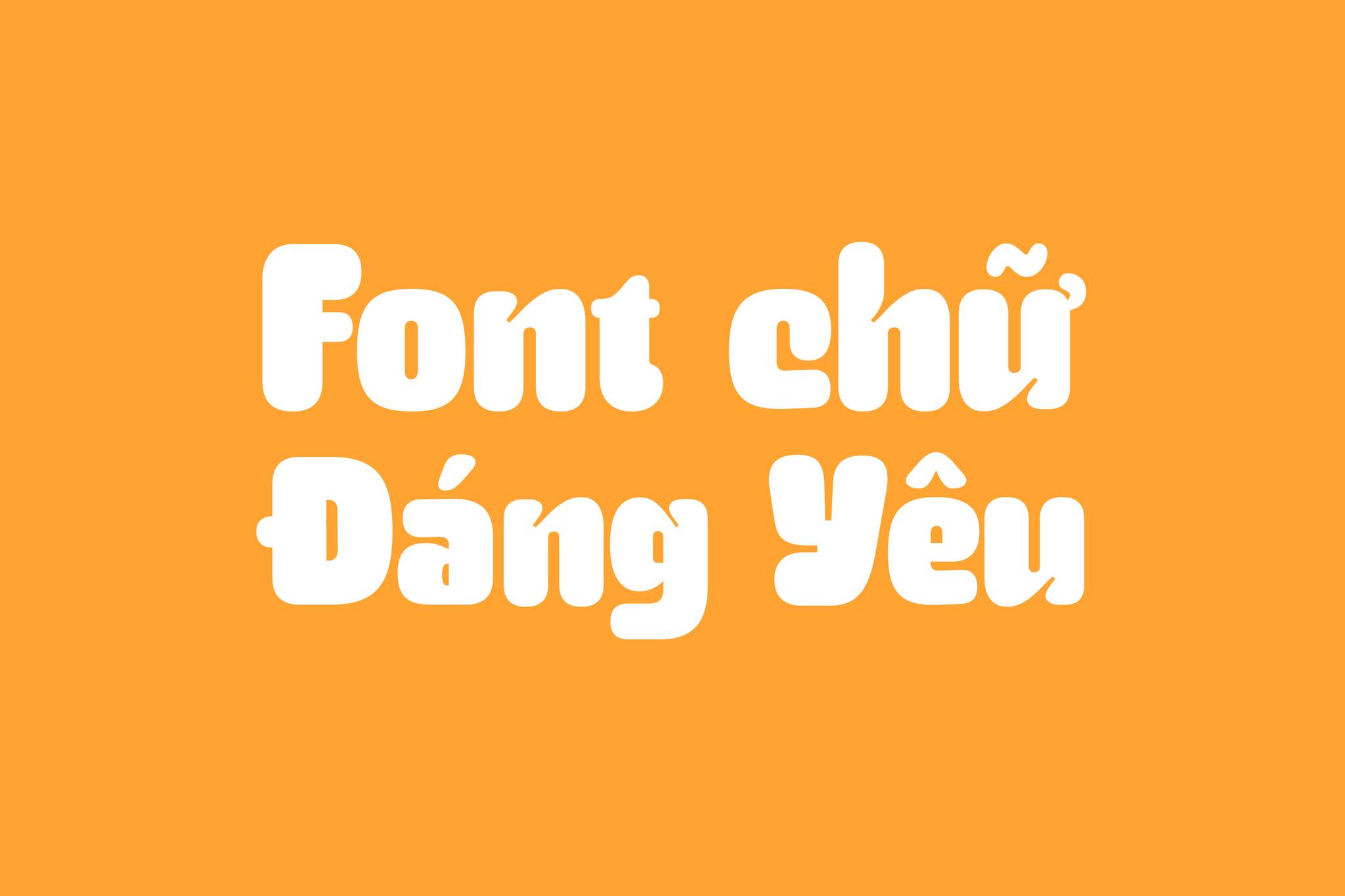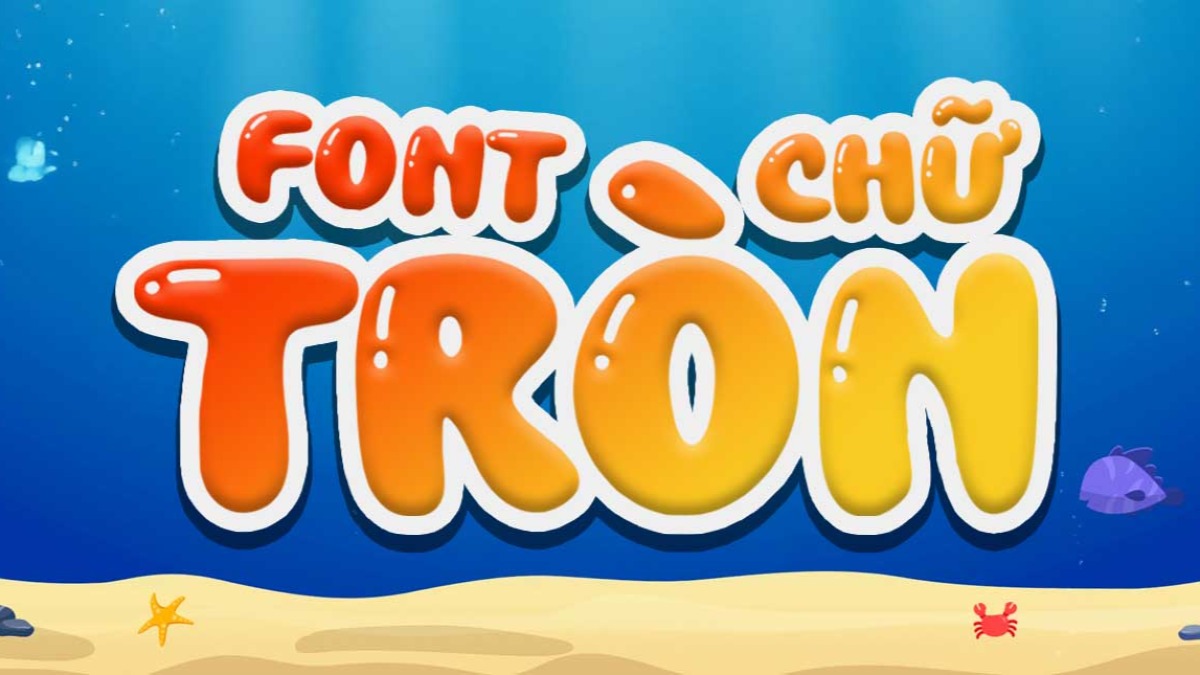
Font chữ tròn mập là nhóm phông chữ có cấu trúc nét dày (bold) và các góc chữ được bo tròn mềm mại thay vì để cạnh sắc nhọn. Trong thiết kế đồ họa, nhóm font này thường được sử dụng để tạo nên cảm giác thân thiện, vui vẻ và cực kỳ hiện đại. Doozypack.vn chia sẻ bộ font chữ bo tròn Việt hóa tuyển chọn, giúp bạn dễ dàng ứng dụng vào thiết kế bao bì, tem nhãn cho các sản phẩm dành cho giới trẻ hoặc trẻ em mà không lo lỗi hiển thị dấu tiếng Việt.
Tại sao font chữ bo tròn lại được yêu thích trong thiết kế bao bì?
Việc lựa chọn kiểu chữ ảnh hưởng trực tiếp đến tâm lý khách hàng khi nhìn vào sản phẩm lần đầu tiên.
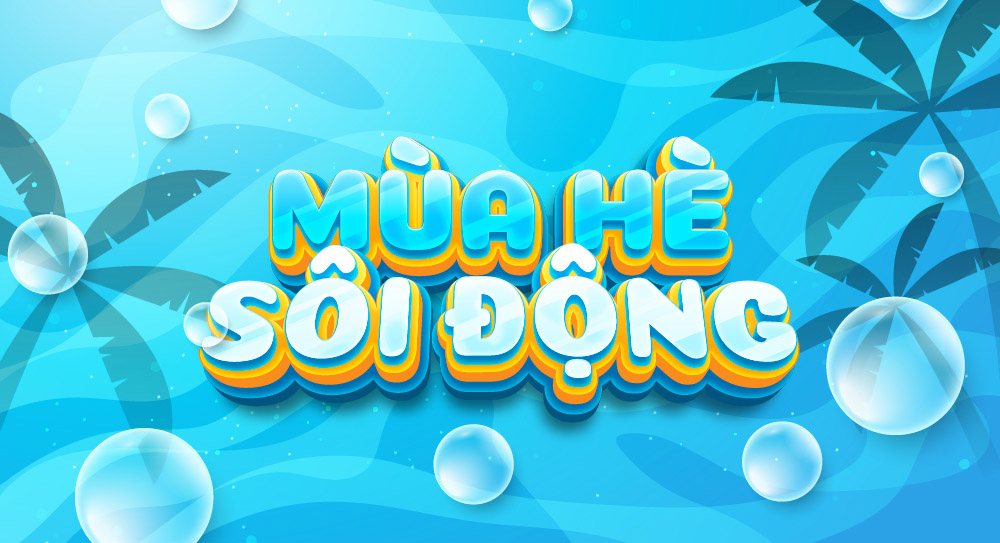
Tạo cảm giác an toàn, gần gũi và không gây áp lực thị giác
Về mặt tâm lý học thị giác, những đường cong bo tròn thường tạo ra cảm giác an toàn, dịu mắt hơn so với các góc nhọn sắc bén. Font chữ bo tròn mang lại vẻ ngoài “organic” (tự nhiên), giúp thương hiệu trông thân thiện, dễ tiếp cận và giàu năng lượng tích cực. Đây là lý do các thương hiệu về đồ tiêu dùng, mẹ và bé hay thực phẩm sạch thường ưu tiên nhóm font này.
Phong cách hiện đại, phù hợp với xu hướng tối giản
Đa số các font chữ bo tròn hiện nay đều thuộc dòng Sans-serif (không chân), mang phong cách tối giản và sạch sẽ. Khi in trên các bề mặt túi giấy hay hộp giấy, font chữ này giúp thiết kế trông gọn gàng, chuyên nghiệp và bắt kịp xu hướng thiết kế phẳng hiện đại của thế giới.
Top bộ font chữ bo tròn Việt hóa đẹp nhất hiện nay
Dưới đây là một số gợi ý font chữ bo tròn việt hóa được các designer đánh giá cao về tính ứng dụng:
- Font Comfortaa: Bộ font quốc dân với đường nét bo tròn tuyệt đối, cực kỳ phù hợp cho các thiết kế mang tính sáng tạo và trẻ trung.
- Font Quicksand: Một bộ font thanh lịch, dù bo tròn nhưng vẫn giữ được sự tinh tế, thường dùng cho các thương hiệu mỹ phẩm hoặc thời trang tối giản.
- Font VAG Rounded: Bộ font cổ điển nhưng vô cùng mạnh mẽ, thường xuất hiện trong các thiết kế logo và bao bì đồ chơi trẻ em.
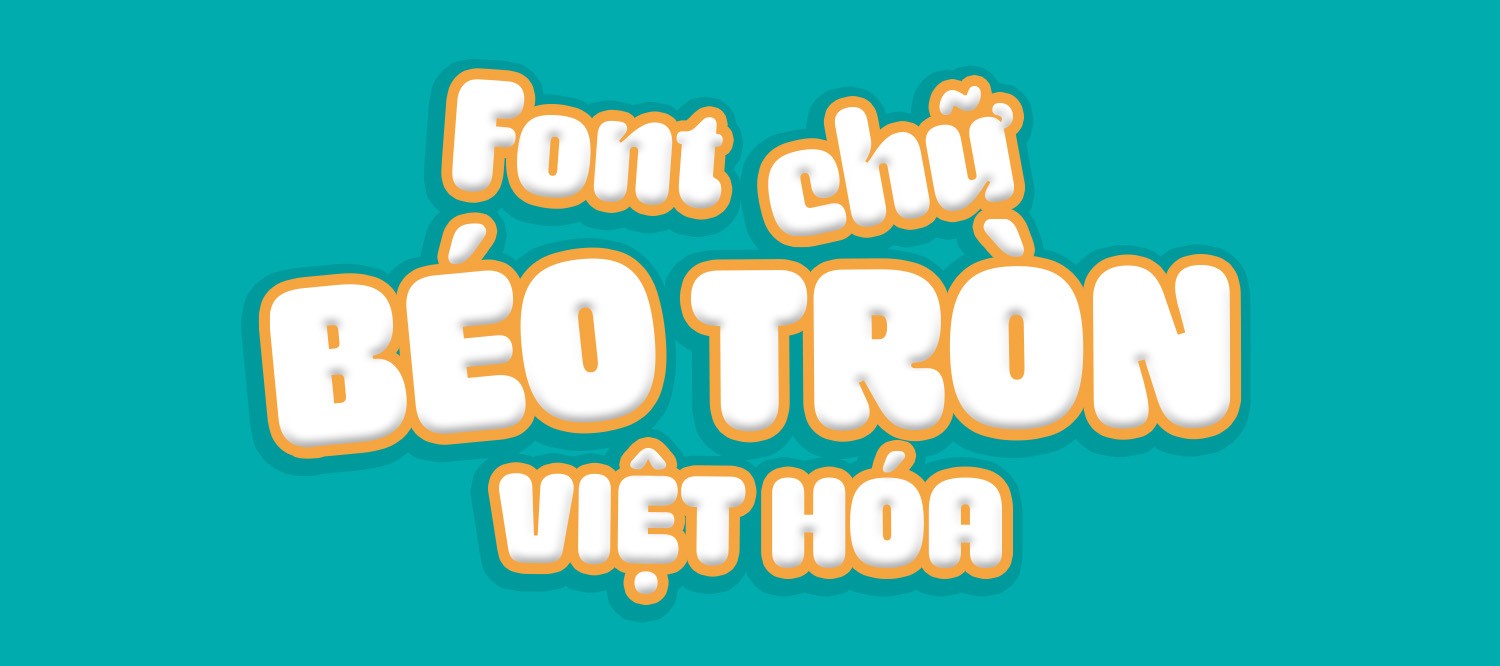
| Nhóm Font | Đặc điểm thị giác | Sản phẩm bao bì phù hợp |
| Tròn mập (Bold/Extra Bold) | Dày dặn, nổi bật | Tên sản phẩm chính trên hộp bánh, tiệm trà sữa, tem nhãn đồ ăn vặt. |
| Bo tròn thanh mảnh | Nhẹ nhàng, hiện đại | Slogan túi giấy thời trang, thông tin hướng dẫn sử dụng sản phẩm. |
| Display Rounded | Phá cách, vui nhộn | Bao bì quà tặng sinh nhật, đồ dùng học tập, nhãn dán trang trí. |
Kinh nghiệm in ấn: Khi sử dụng font chữ tròn mập có nét cực dày, bạn nên tăng khoảng cách giữa các chữ cái (tracking) thêm một chút. Việc này giúp các nét bo tròn không bị dính vào nhau khi mực in thấm vào giấy, đảm bảo chữ luôn rõ nét và dễ đọc.
03 Ứng dụng của font chữ tròn mập trong sản xuất bao bì giấy
Font chữ bo tròn tạo nên những hiệu ứng cảm xúc rất tốt trên thành phẩm in ấn thực tế:
- Tem nhãn đồ uống và thực phẩm: Sự tròn trịa của phông chữ tạo cảm giác “ngon mắt”, kích thích vị giác, rất hợp cho các loại tem dán chai trà sữa, hũ thực phẩm sấy khô.
- Hộp giấy đựng sản phẩm trẻ em: Font chữ tròn mập mang lại sự an toàn và đáng yêu, giúp bao bì đồ chơi hay quần áo trẻ em trở nên thu hút hơn đối với cả phụ huynh và trẻ nhỏ.
- Túi giấy quà tặng: Một thông điệp ngắn gọn bằng font bo tròn in trên túi giấy Ivory cán mờ tạo nên vẻ ngoài hiện đại và tràn đầy cảm hứng.
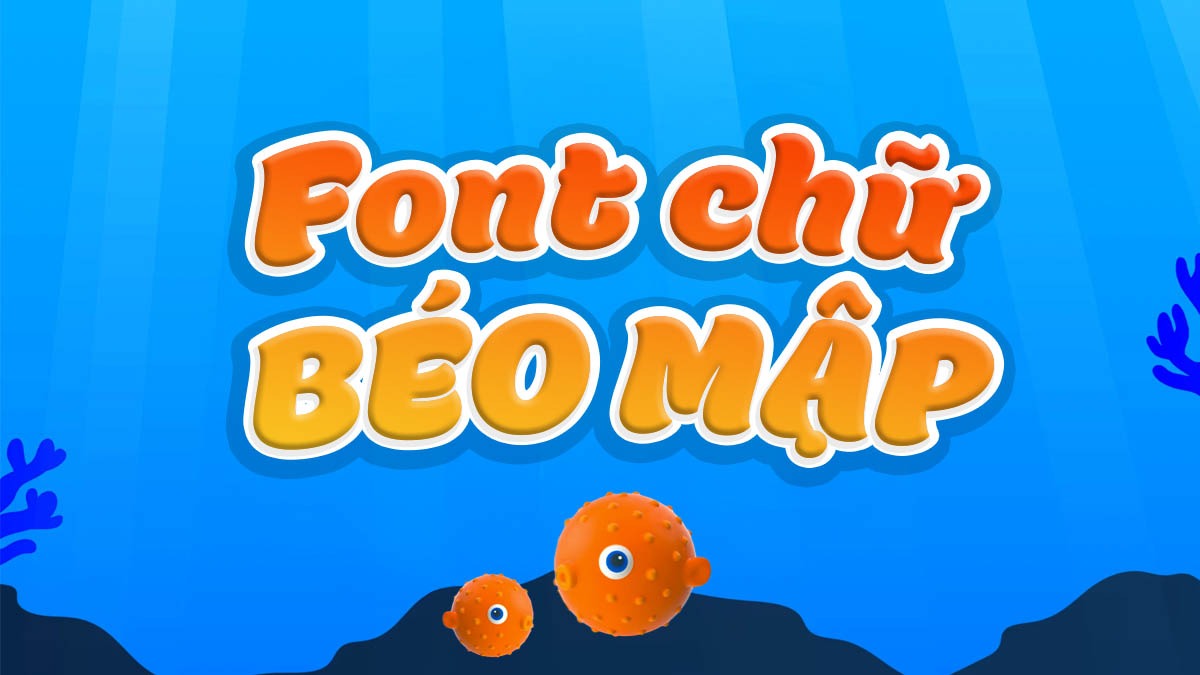
In ấn font chữ nét dày và bo tròn cần sự am hiểu về kỹ thuật sản xuất để thành phẩm đạt độ sắc nét:
- Hiện tượng bết mực: Với các font chữ quá mập, khoảng trắng bên trong các chữ cái như “o, a, b, d” thường rất nhỏ. Nếu in trên giấy Couche bóng mực dễ bị loang nhẹ, bạn cần kiểm tra file kỹ để tránh các lỗ chữ bị lấp đầy bởi mực.
- Kích thước chữ tối thiểu: Đối với font bo tròn nét mảnh, không nên để kích thước dưới 6pt khi in trên giấy Kraft hoặc giấy mỹ thuật có gân, vì nét bo ở các góc dễ bị mờ hoặc mất nét.